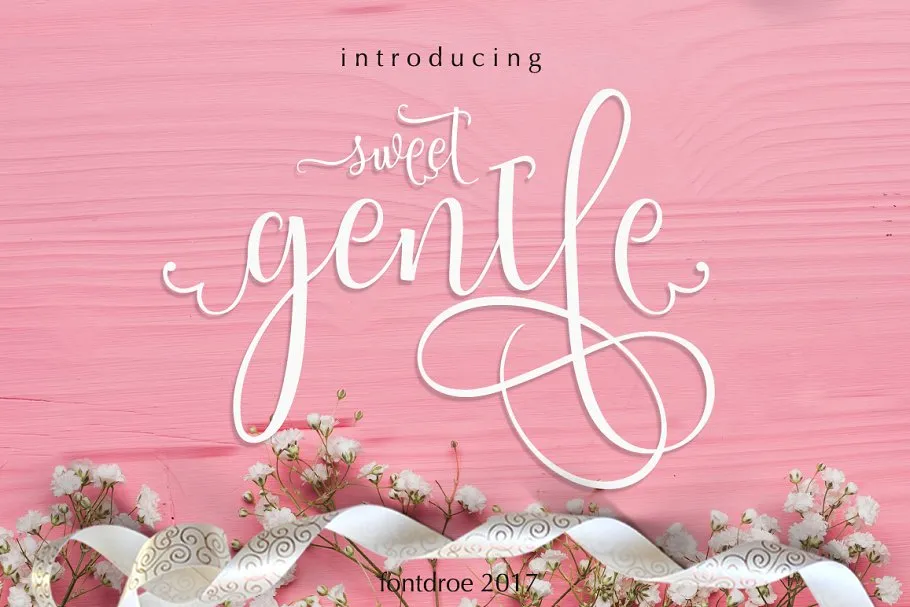
Sweetgentle Script Font – Download Grátis
A Sweetgentle Script Font é uma nova fonte de calligrafia feita à mão que oferece harmonia tipográfica para um vasto leque de projetos design. Esta fonte moderna, desenvolvida pelo Designer 24Design, é uma mistura perfeita de elegância e simplicidade, ideal para criar design em diversos formatos. SWEETGENTLE não apenas oferece uma variedade inigualável de caracteres (750), mas também uma abordagem versátil que inclui criação de logotipos, cards de presentes, convites para casamentos, subtítulos, assinaturas, camisetas personalizadas, documentos de bordados e muitos outros usos imagináveis. A Sweetgentle Script Font está disponível em sua categoria de fontes de calligrafia, como uma opção única que pode enriquecer qualquer projeto design, com um toque moderno e agradável. Seja para criar algo delicadamente personalizado ou fazer uso de seu design originalmente chamativo, este é definitivamente um ícone que torna o trabalho na linha.